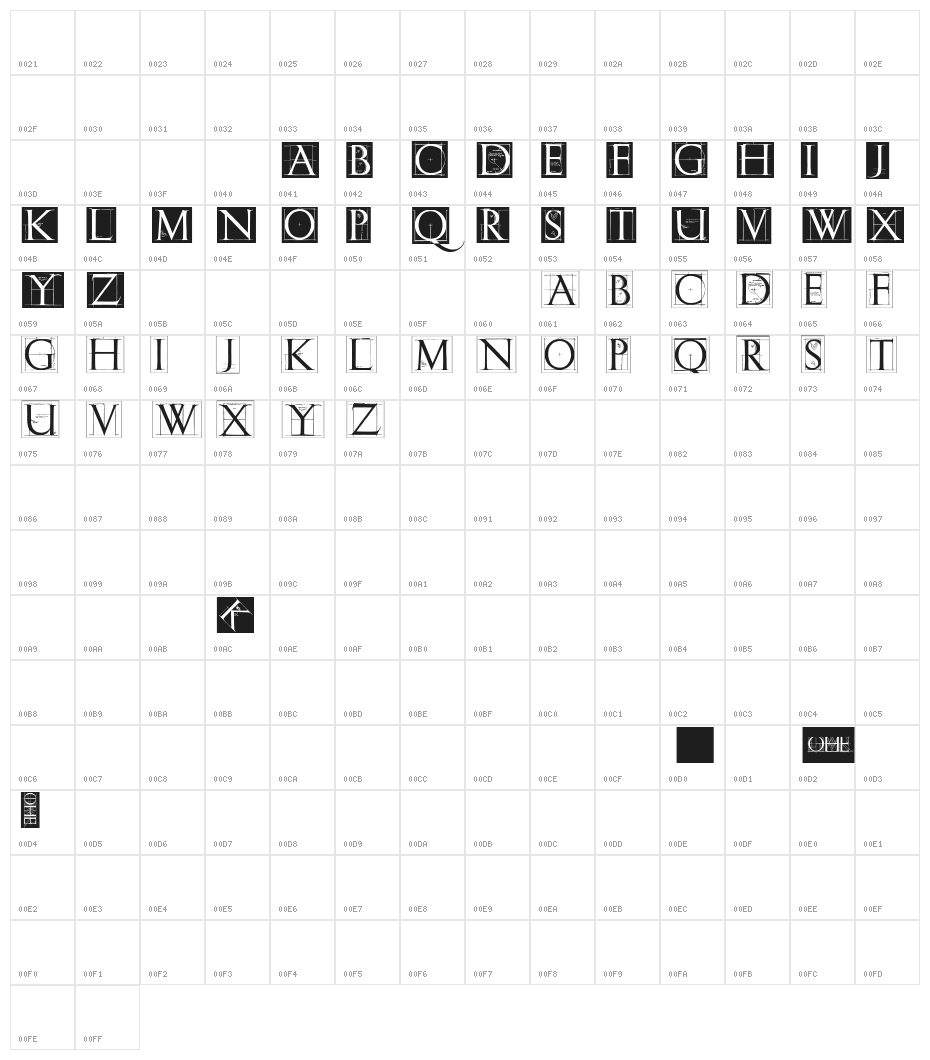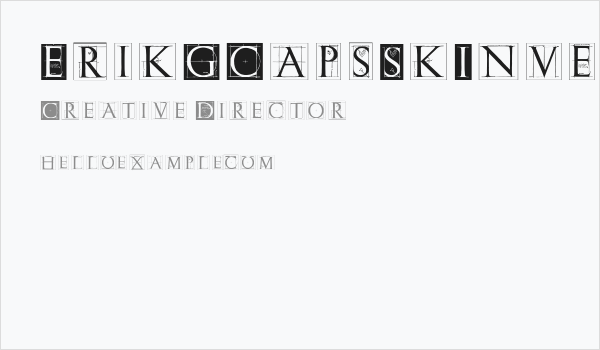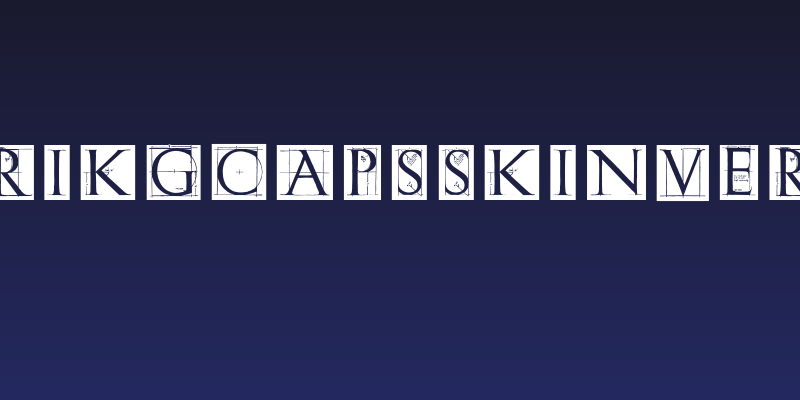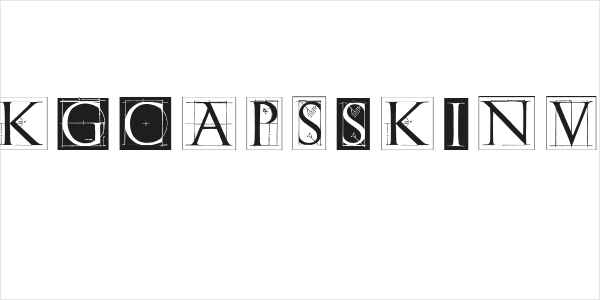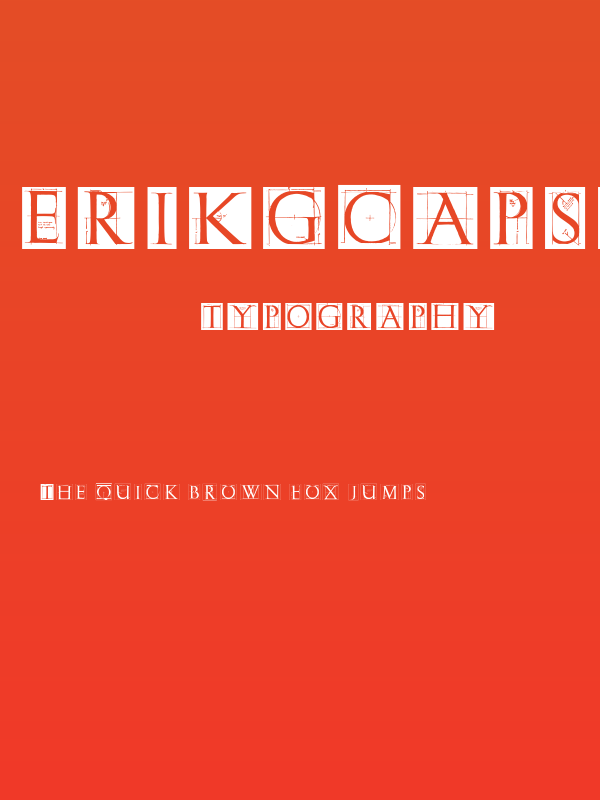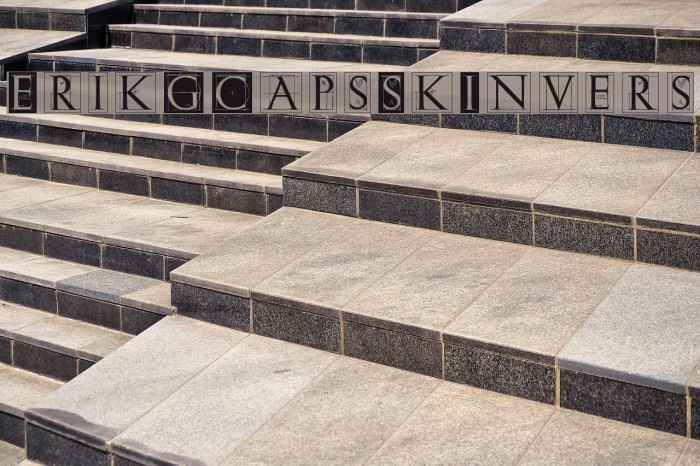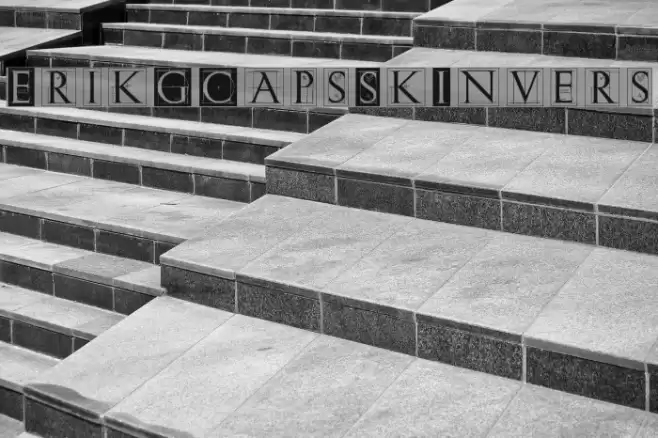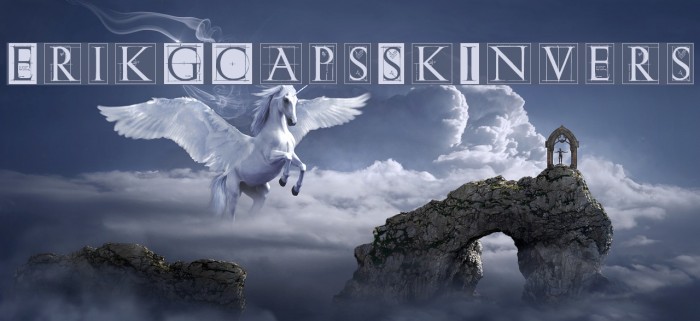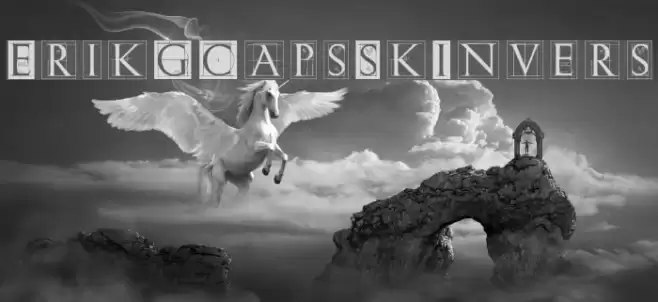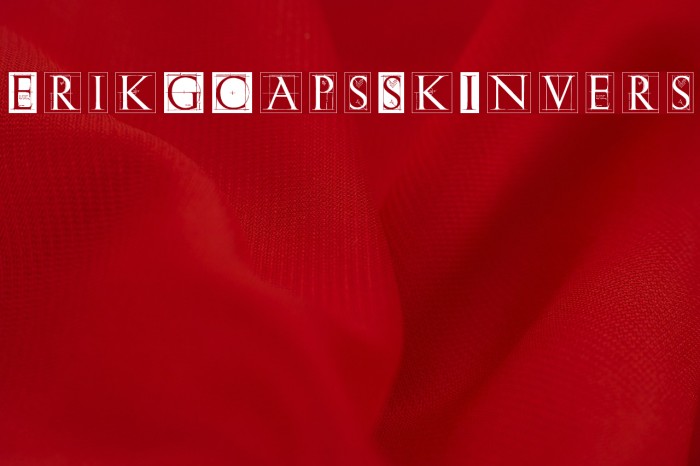
ErikGCapsSkInvers Font
| Gesamtstil | Vintage |
| Vorgeschlagene Projekte | This font is perfect for projects that require a historical or vintage touch, such as book covers, posters, branding for travel-related businesses, or any design that benefits from a decorative and classic aesthetic. |